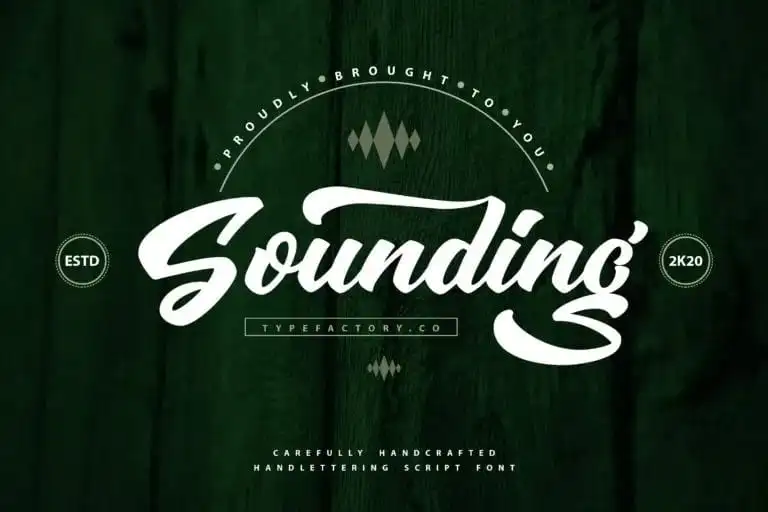
Sounding Script Font – Download Grátis
A Sounding Script Font é uma excelente escolha para quem procura uma fonte script que transmite leveza e elegância, inspirada nas linhas reais feitas com pincel e tinta. Esta fonte traz a sensação de liberdade e confiança no formato dos caracteres, criando um estilo natural e feminino. Perfeita para projetos onde você quer expressar sutileza e coragem, esta font é ideal para criação de logotipos, título e designs de revistas ou publicações. Se você busca uma fonte que transmita essencialmente feminilidade, atrevimento e liberdade criativa, a Sounding Script Font é um excelente investimento. Criada pelo designer Type Factory, este tipo Script é perfeito para projetos que vão desde criar citações até desenvolver designs esportivos ou de estilo de vida.